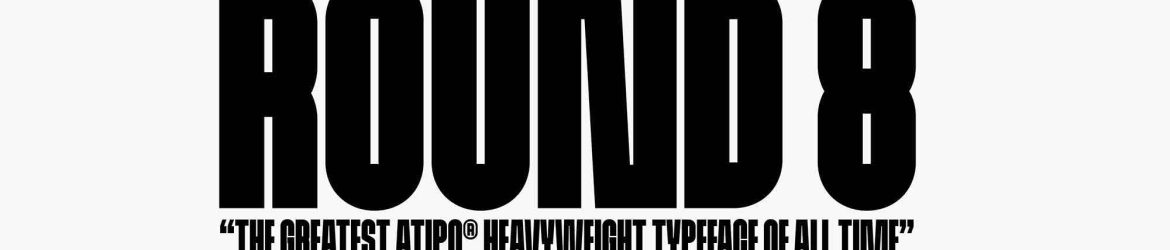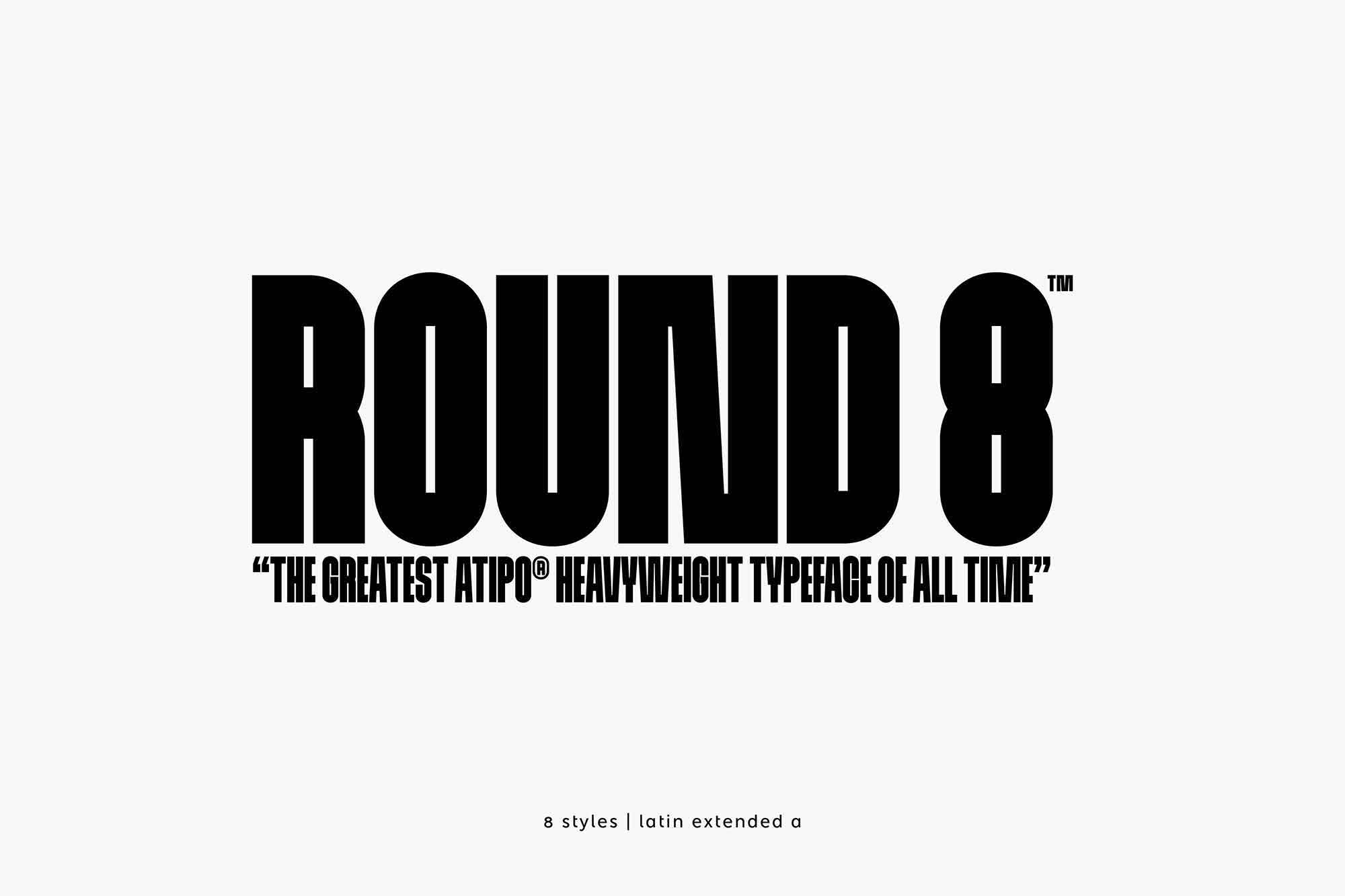
Round 8 Heavyweight Font é uma fonte de tração poderosa que traz caracteres bem definidos e uma estrutura compactada. Sua aparência tem raízes na famosa luta de boxe que se definiu no oitavo round. As letras do tipo têm uma visibilidade óptica significativa, o que as torna perfeitas para chamar a atenção do leitor, tornando-as ideais para headline, design de panos ou capas de revista. Com um visual poderoso e singular, este recurso gráfico é uma excelente escolha para ilustrar suas criações de design. Engane-se, essa fonte está repleta de potencial para transformar seus designs em elementos de destaque.